原标题:字体设计大师Ed Benguiat去世,曾设计600多款字体,不少从80年代流行至今
10月15日,著名美国平面设计师、字体设计大师Ed Benguiat在新泽西州家中去世,享年92岁。与他有过密切交集的《纽约时报》、纽约视觉艺术学院都纷纷发出讣告追念。
Benguiat是美国平面设计协会AGI成员、纽约字体指导俱乐部(Type Directors Club,简称纽约TDC)前任主席,一生设计了600多种字体。1989年,他因在字体设计方面的杰出成就获得了纽约TDC颁发的Gold Medal for Excellence奖章,1990年又获得由美国罗彻斯特理工大学颁发的Fredric W. Goudy奖。这位设计师对字体设计行业的贡献仍历历在目,Design360°在这里和大家简单回顾他的设计生涯。
Ed Benguiat于1927年出生,在纽约布鲁克林一个普通家庭中长大。母亲是红十字会的司机,父亲是曼哈顿下东城Bloomingdale’s百货公司的设计总监,9岁的他所拥有的最多玩具就是来自父亲的钢笔、画笔和制图工具。
2岁的Benguiat
直到10岁时收到父亲送的一套爵士鼓以后,Benguiat迷上了打鼓。第二次世界大战期间在空军团服完兵役后,他再次捡起爵士乐手这个身份,与Stan Kenton和Woody Herman等乐手组成合奏团一起演奏,成为了一名杰出的爵士乐手,全心投入寻找在纽约的各种地下俱乐部和酒吧演出的机会。
直到一次去音乐家工会缴纳会费时,Benguiat看到正在参加礼拜仪式的老人后联想到自己的未来可能也是这副模样,转念决定成为插画家。他当时演出所在的俱乐部位于第五大街附近,大街上有一所艺术工作坊的标语写着“Be an Artist” ,这吸引了他向新的领域展开尝试。在这所Paul Standard旗下的广告艺术工作室学校,Benguiat尝试了绘画、排版、设计、字体和书法,重新跟上父亲的步伐走上了设计的道路。
TDC采访中Benguiat提到在纽约演出过的俱乐部3DEUCES
在TDC的采访中,Benguiat表示自己看到了早期的音乐生涯与后来做设计之间的联系。他说:“音乐对我来说便是按照正确的顺序放置音符,使它们悦耳,平面设计也是如此,需要按照正确的顺序放置事物使它们看起来令人愉悦。”
毕业后,Benguiat在各种出版社、工作室和广告公司担任设计师。随着经验的累积,他在1953年得到了担任时尚杂志《Esquire》副视觉总监的机会,并在纽约开设了自己的设计工作室。
1962年,他加入了最早一批使用摄影技术生产商业字体和刻字的字厂Photo-Lettering Inc.,担任版式设计总监,为其设计了400多种字体,并为各种类型的客户设计或再设计字体LOGO,福特、雅诗兰黛、AT&T、《花花公子》等都是他的合作对象。
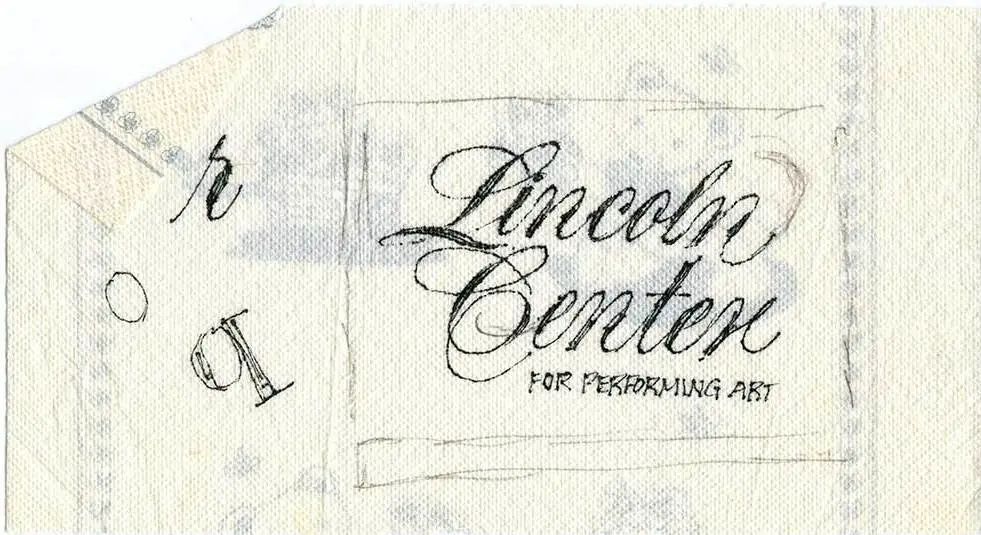
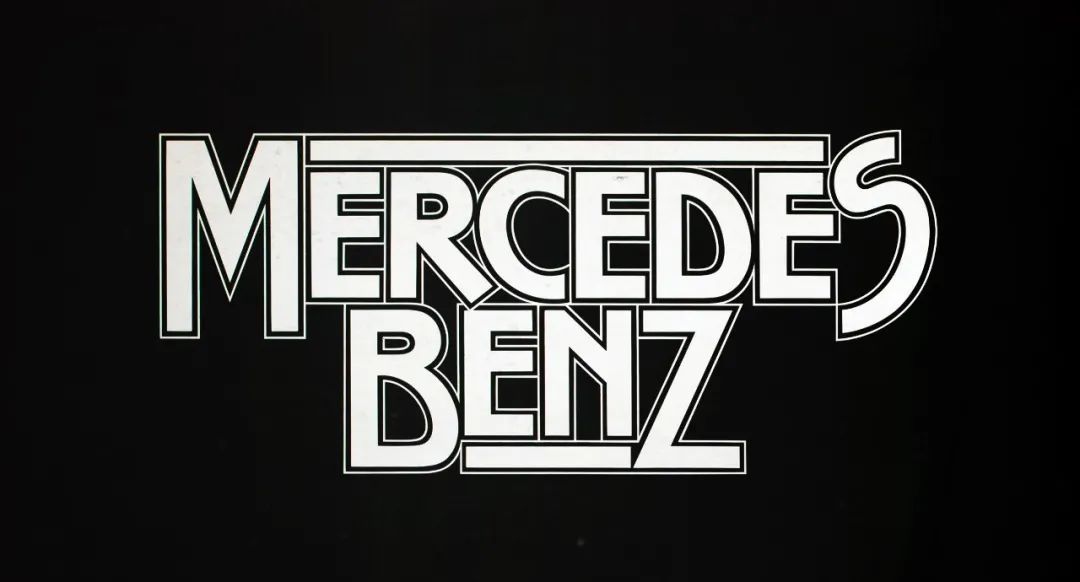
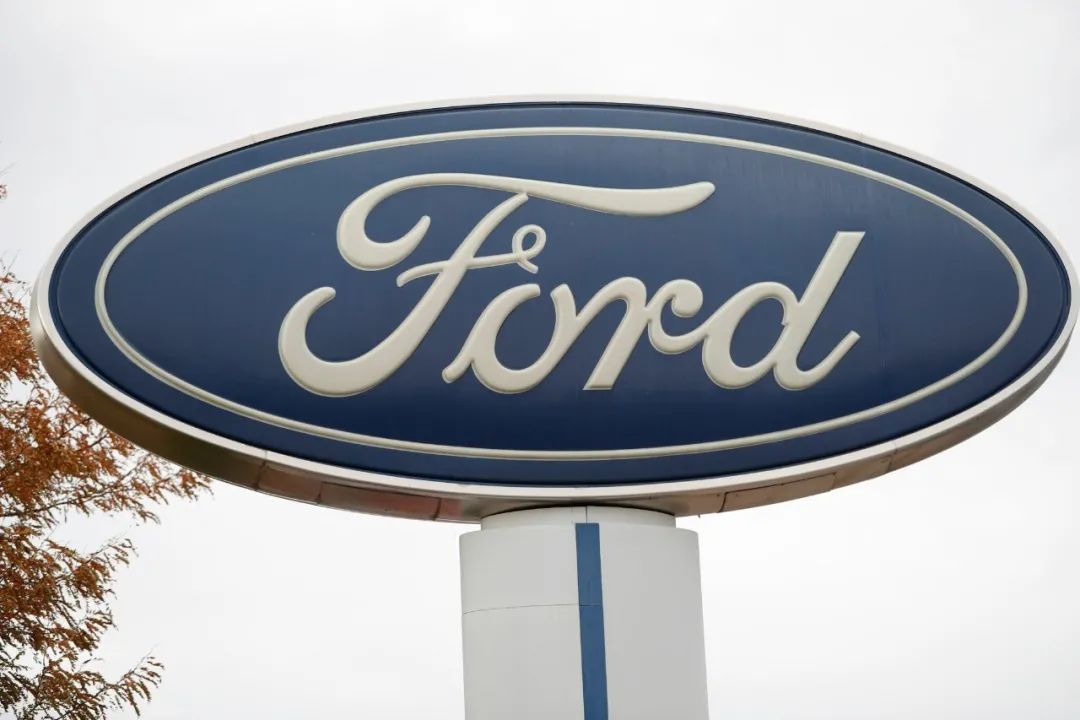
Benguiat曾参与福特、奔驰LOGO设计
1967年,《纽约时报》当时的艺术总监Louis Silverstein被赋予重新调整报纸标头的任务,那时他在方格纸上重新绘制了新LOGO,并聘请Benguiat完善这个设计。这个为《纽约时报》重新设计的LOGO也让Benguiat为更多人所知。
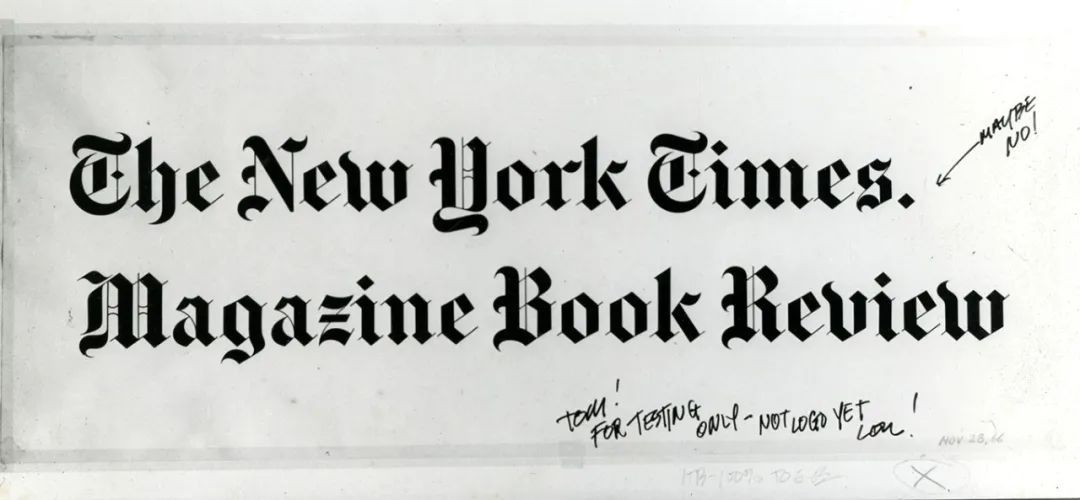
《纽约时报》再设计手稿
Benguiat并没有按照艺术总监的想法完全改变这个LOGO的设计,而是选择对其修复并在细节上进行改版。他觉得LOGO本身已经太具标志性,如果更改它的话将没人认出它,因此接受这点并修改它,是Benguiat认为的最佳选择。
手工绘制LOGO出身的Benguiat,常需要一年的时间去发展一款字体,这种切身的设计经验,也让他对字体的复杂性有了更多层次的理解。纽约时报的编辑Neil Genzlinger形容道,“Benguiat了解一个成功的设计不仅关于单个字母的造型,而是更多由字母之间的间距决定。而且他知道,当字体被放大到广告牌大小时,计算机屏幕上看起来不错的内容可能无法起到相同的效果。”
1960年代中期,Benguiat开始在纽约视觉艺术学院任教,长达近50年。正是他在字体设计和LOGO再设计方面的成就和对教学的贡献,使他成为行业中备受尊敬的人物。不过,Benguiat对设计界的影响并不只停留在设计的部分,他也参与推动了字体走向市场,被更多行业所重视并使用。
Benguiat在进行教学
1971年,Benguiat加入了由设计师Herb Lubalin、Aaron Burns和Ed Ronthaler组成的公司 ——The International Typeface Corporation(国际字体公司,简称ITC),和ITC共同开启字体生产行业。ITC是市面上第一家为字体设计师提供服务的公司,他们也是最早一批有意将字体设计向市场推销的设计师。
在这里工作期间,Benguiat设计了一系列经典字体,包括Tiffany、Benguiat、Benguiat Gothic、Souvenir、Korinna、Panache、Modern No. 216、Bookman、Caslon No. 225、Barcelona、Avant Garde Condensed等。成为副总裁后,他与Lubalin又合作创建了ITC备受赞誉的杂志《U&lc》。
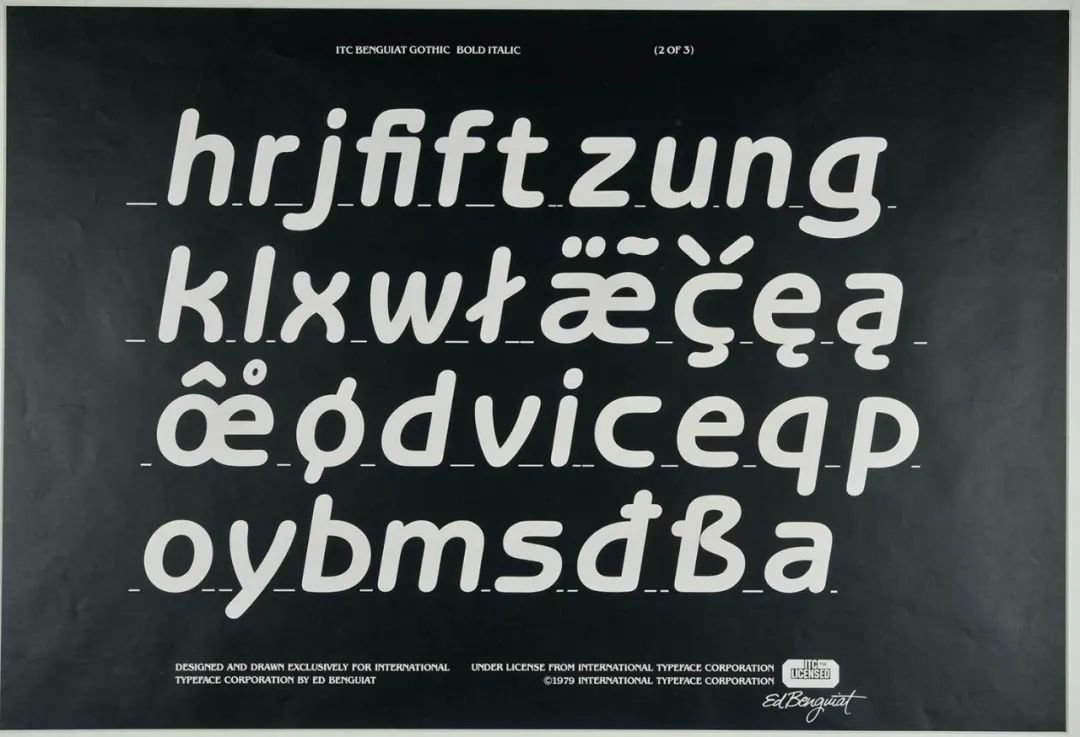
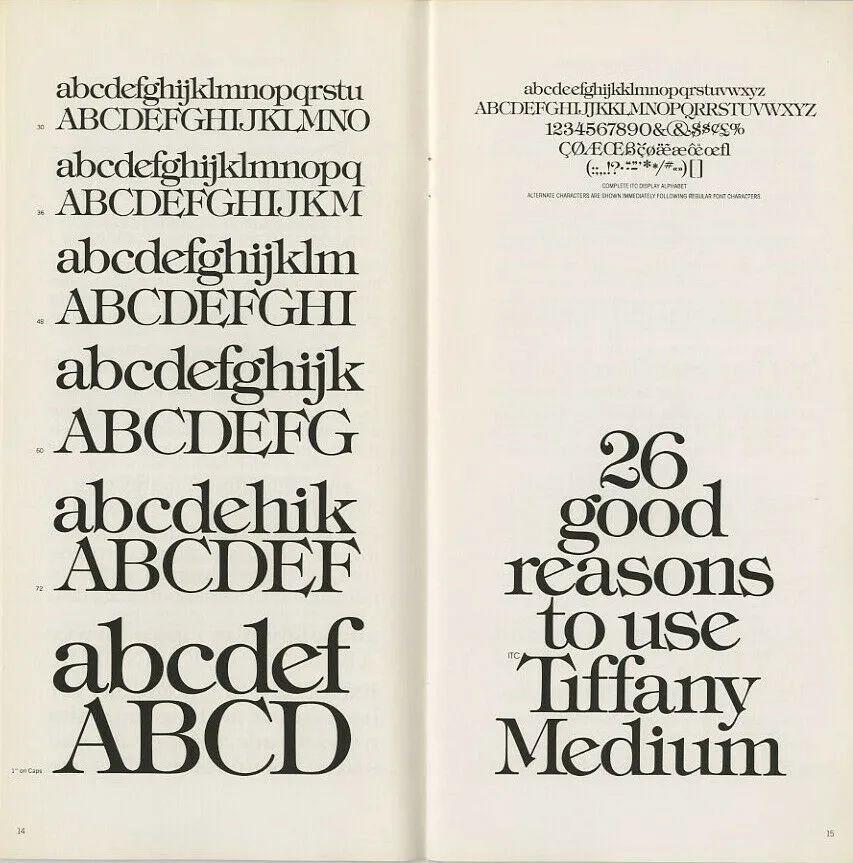
纽约视觉艺术学院收藏档案中的Benguiat字体设计手稿和手册
1975年至1977年期间还有一个有趣的花边新闻,那时生活在纽约的Benguiat常与电影导演伍迪·艾伦(Woody Allen)在同一家新泽西餐厅用餐。有天早上艾伦向Benguiat询问应该为自己即将上映的电影搭配什么字体, Benguiat给他推荐了一款并非自己设计的Windsor字体。从此之后,Windsor就一直被用于Woody Allen的电影中。
随着字体设计在不同领域的推广,由Benguiat设计的字体开始出现在各种电影的标题设计中,比如1968年的科幻片《人猿星球(Planet of the Apes)》、1972年的《超级苍蝇(Super Fly)》和1997年由昆汀·塔伦蒂诺(Quentin Tarantino)导演的电影《危险关系(Jackie Brown)》。
《人猿星球》《超级苍蝇》《危险关系》电影片头或海报中的字体皆出自Benguiat
不过Benguiat在ITC期间创造的最受欢迎的字体,应该是1978年首次发行的ITC Benguiat。
ITC Benguiat设计手稿
那时Benguiat本打算创作出一款漂亮且易读的字体,但在1980年代初,这款字体受到了著名恐怖小说家斯蒂芬·金的喜爱,出现在他早期大量小说封面的标题上,从《魔女嘉莉》《闪灵》再到《IT》……这些将ITC Benguiat用在封面标题的小说不仅被大量书迷收藏,也为这款字体赋予了一层专属的惊悚气息。
斯蒂芬·金小说封面
近年来,建构在80年代风潮及故事上的美剧《怪奇物语(Stranger Things)》再次选择了这款字体用作片头和标题设计。这部美剧以不同的方式和风格重新设计使用它,也让ITC Benguiat字体再次回到大众视线中,让更多年轻人认识到了这位设计师。
Benguiat曾表示,字体在1980年代流行起来并不困难,因为那时大约只有15种系统字体可供大众使用。从《危险关系》《怪奇物语》等影片便可看出,这款Benguiat同名字体却并非只是80年代昙花一现的流行,而是从那之后一直流行到90年代甚至现在。
此外,1987年的科幻片《星际迷航:下一代(Next Trek:The Next Generation)》以及派拉蒙影业(Paramount Pictures)所有VHS录像带开头的版权声明,都可以见到这款ITC Benguiat字体。
《星际迷航》片头字体同为ITC Benguiat
这款反复流行并被使用的字体案例足以说明Benguiat设计的经典性,他曾谈到对字体设计的理解是这样的,“我不认为字体一定是可读的。它应该是漂亮的。(I do not think of type as something that should be readable. It should be beautiful.)”对这种设计理念的坚持在强调可阅读性的字体设计世界中尤为少见。
Benguiat在访谈中曾讲过,“长时间做某事并不意味着你做得很好,它只意味着你已经做了很长时间了。无论何时完成一个作品,我仍会有‘当初明明可以做得更好’的遗憾感(No matter when it’s finished, I still say, ‘should-a, could-a, would-a.’)。”